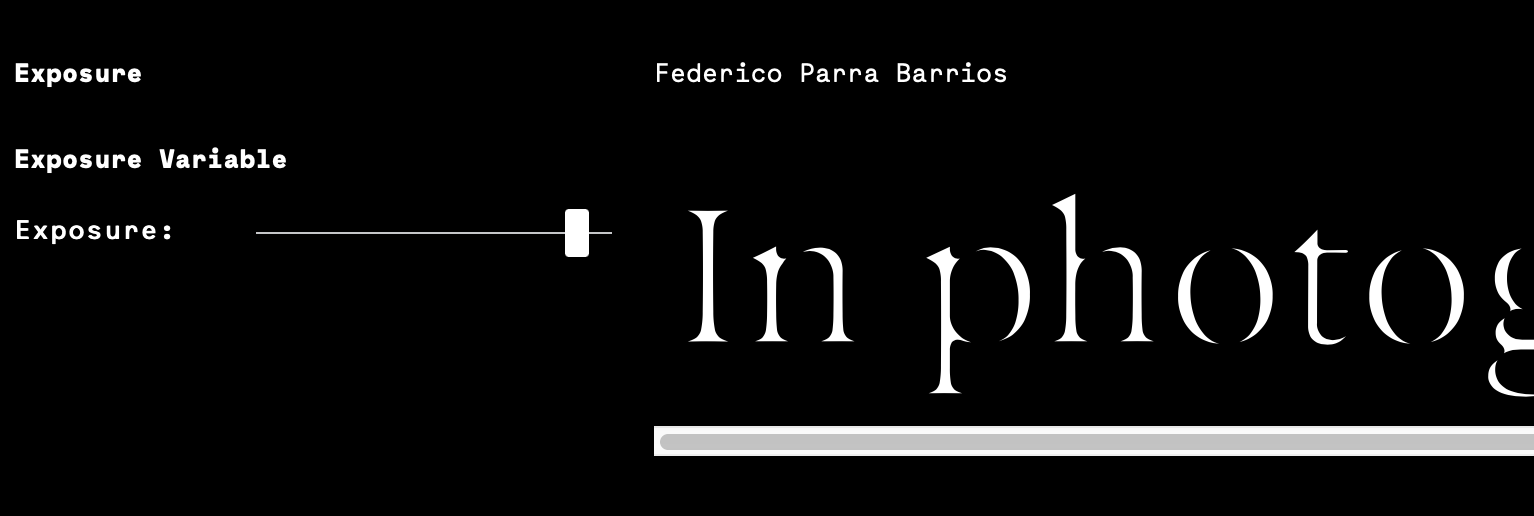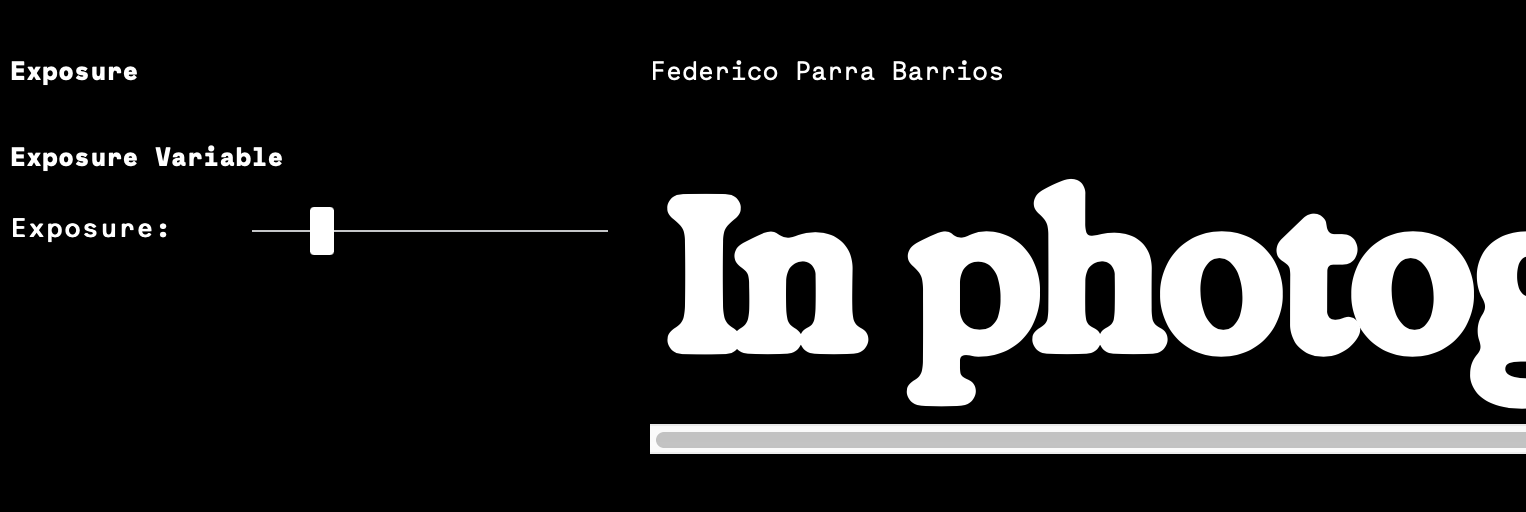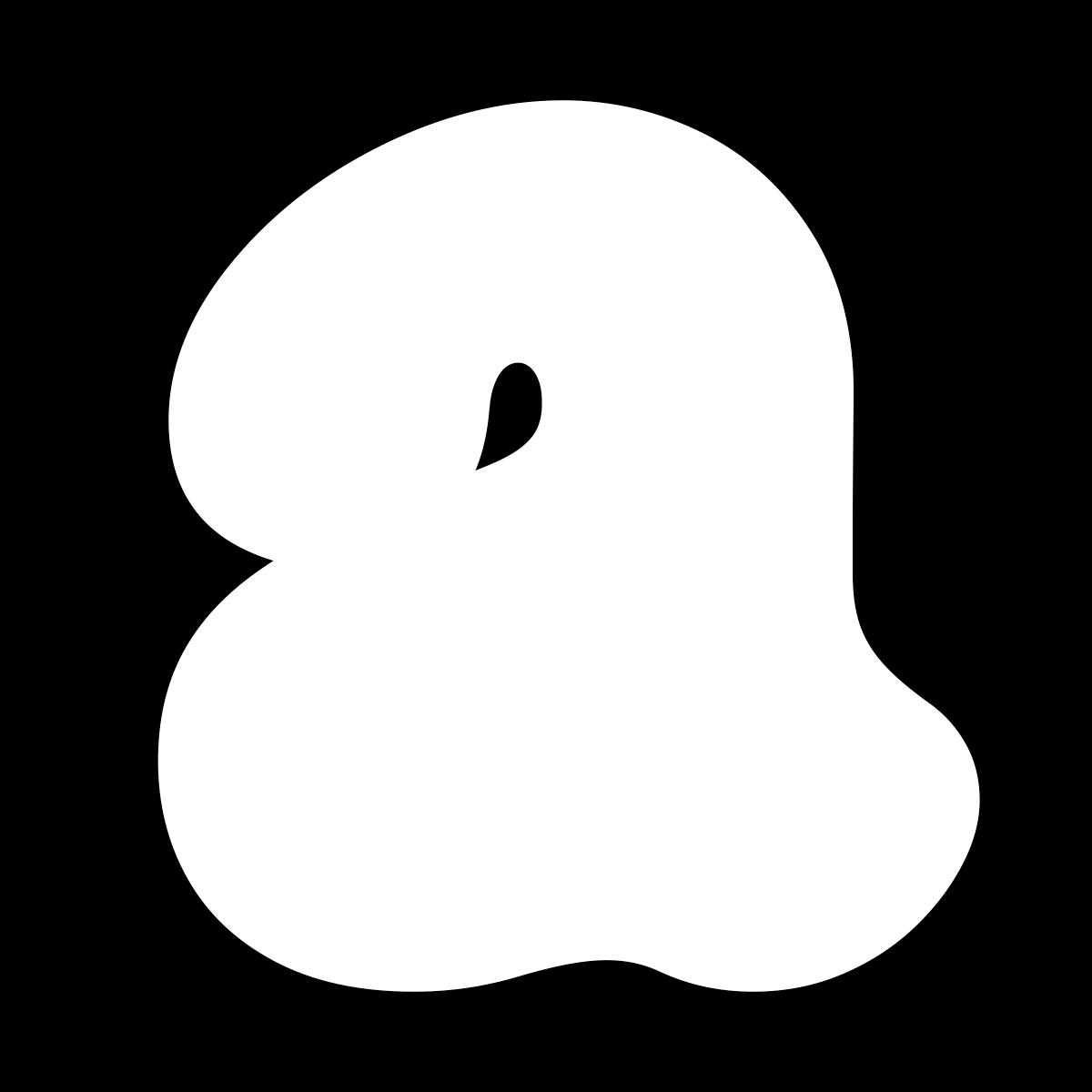
Ich finde sie sehr viel origineller und charmanter als das Gros der Hipster Grotesken (die ich oft nicht auseinanderhalten kann) ...
Stimmt schon … allerdings bekomme ich Nackenschmerzen, wenn ich das kleine a angucke :shock:
Du meinst Farbe ist das neue Hipster?
So würde ich das nicht sagen. Aber Schrift wird ja nun mal fernab des Fließtextes sehr oft farbig eingesetzt – weshalb also nicht auch in Musteranwendnungen mit Farben arbeiten? Farbe und Minimalismus schließen sich ja auch nicht aus – auch wenn der Zeit-Artikel etwas anderes suggeriert.
allerdings bekomme ich Nackenschmerzen, wenn ich das kleine a angucke
Dir kann geholfen werden! :cheer:
Ja wer hat denn da das Weinglas auf dem ı stehen lassen?
Typisch Franzosen ...
Auf dem u stehen dann 2?
Und wie halten die sich auf a und o?
Bei mir verändern die Schieberegler leider gar nichts :-?
Das Profil-G für ordentlich Grip …
Das ist so holzhammermäßig, dass es schon wieder gut ist. :-D
Hast Du diese Animation erstellt?
Die Animation ist aus dem Newsletter der Foundry ... auf der Website hab ich sie allerdings nicht gefunden.
metal umlauts auf dem ß
Ich scheine irgendeine Autokorrektur im Auge zu haben; ich las zweimal »Schlöß«, bis mir beim dritten Mal auffiel, dass die Punkte ja doch nicht über dem o sitzen … 🙄